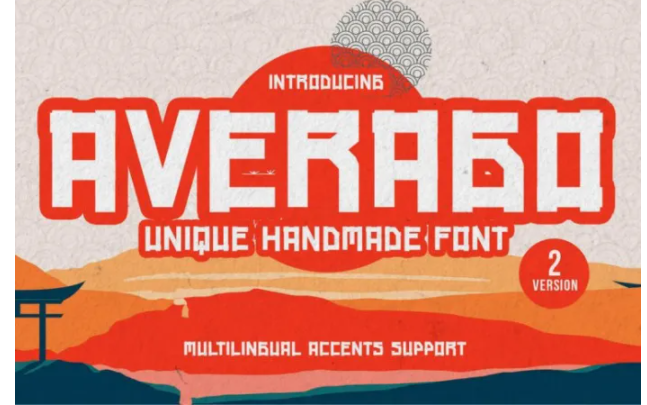
Представляем наш новый продукт Averago - уникальный шрифт ручной работы, который придаст вашему дизайну современный вид.
Может облегчить передачу сообщения в вашем дизайне. Используйте его для создания потрясающих надписей, этикеток, киноэкранов, постеров, названий фильмов, цитат, плакатов, DIY проектов, брендинга, упаковки, поздравительных открыток, веб-сайтов, фотографий, наложения фотографий, знаков, витрин, бирок и многого другого!